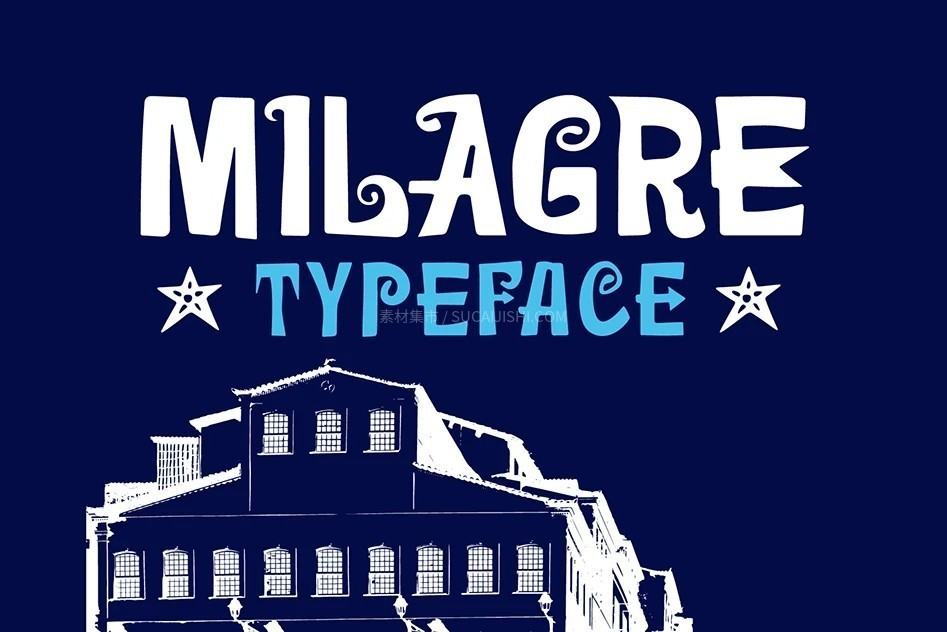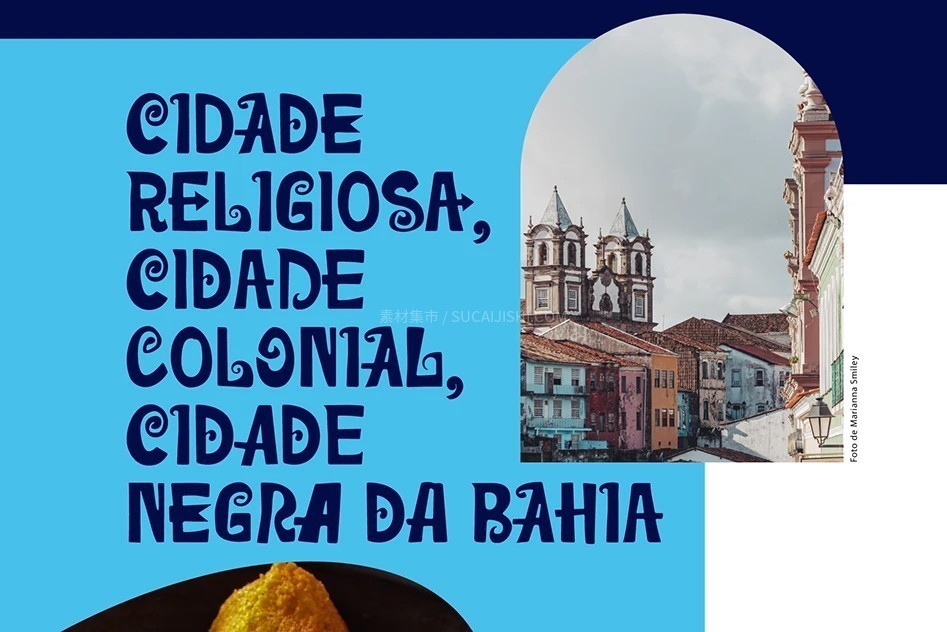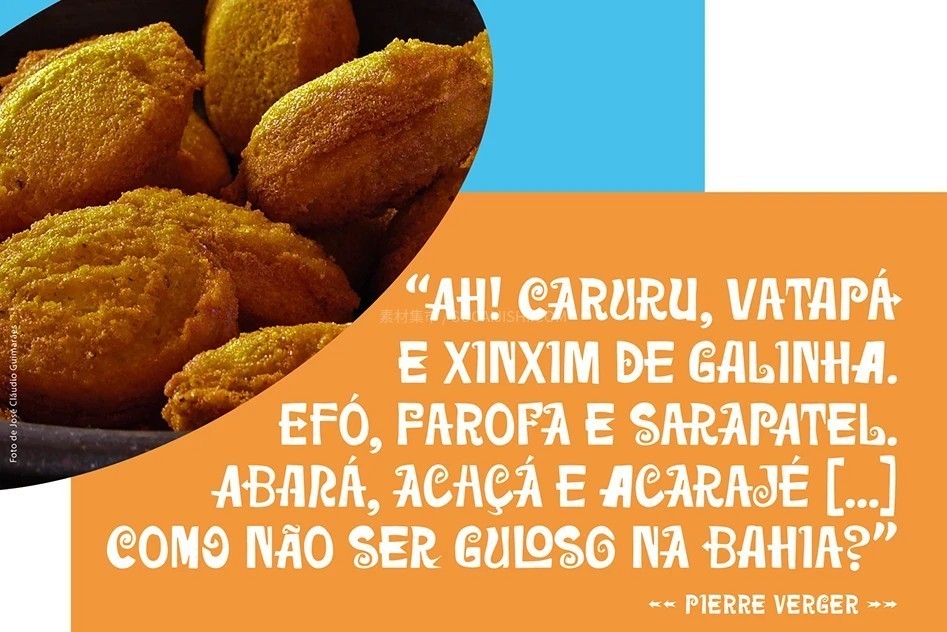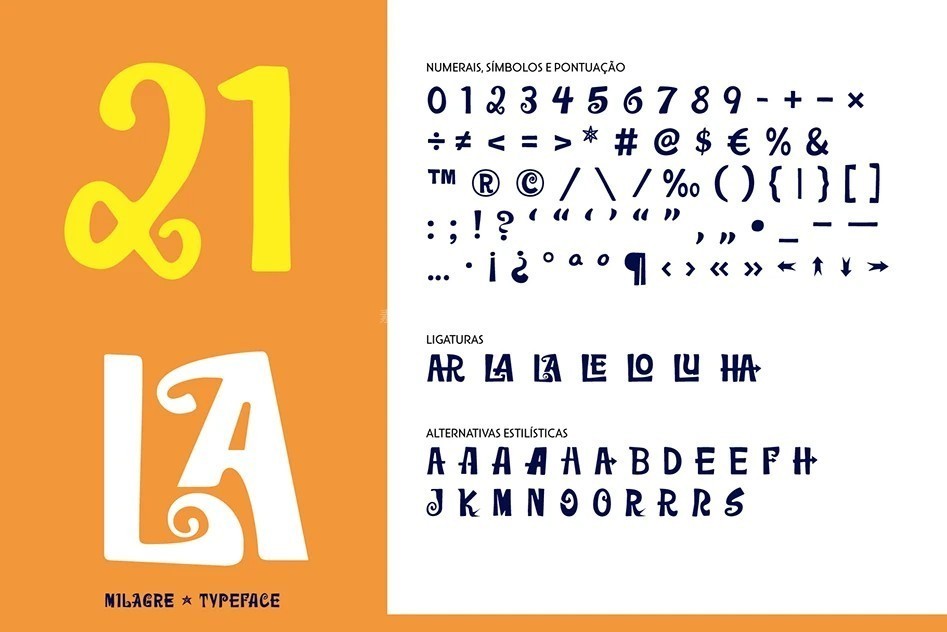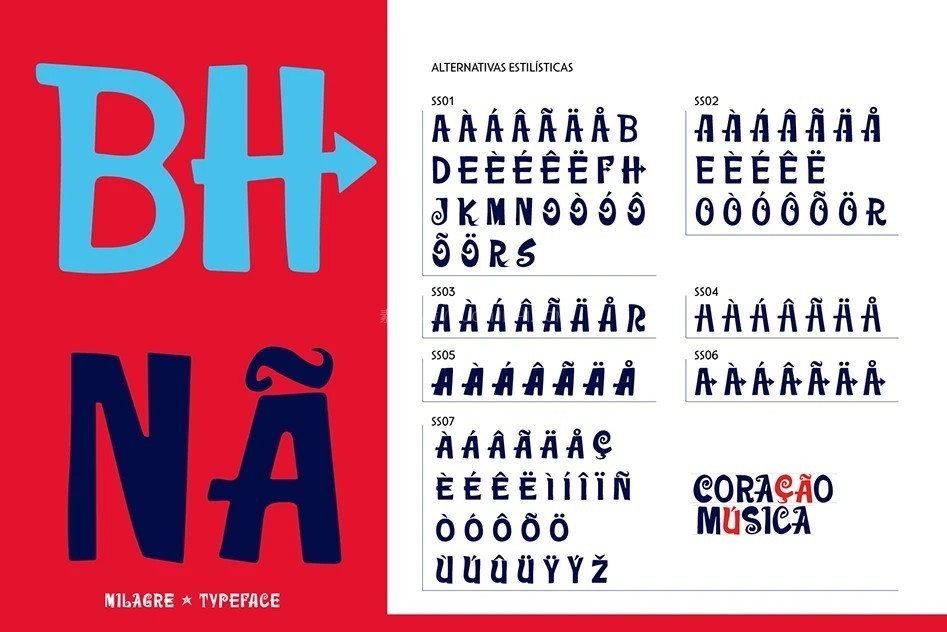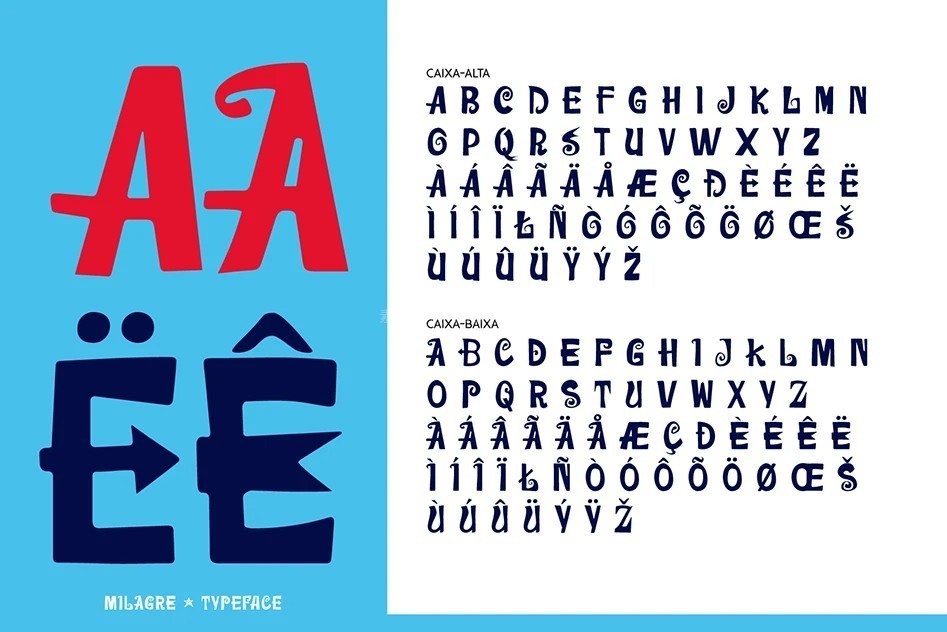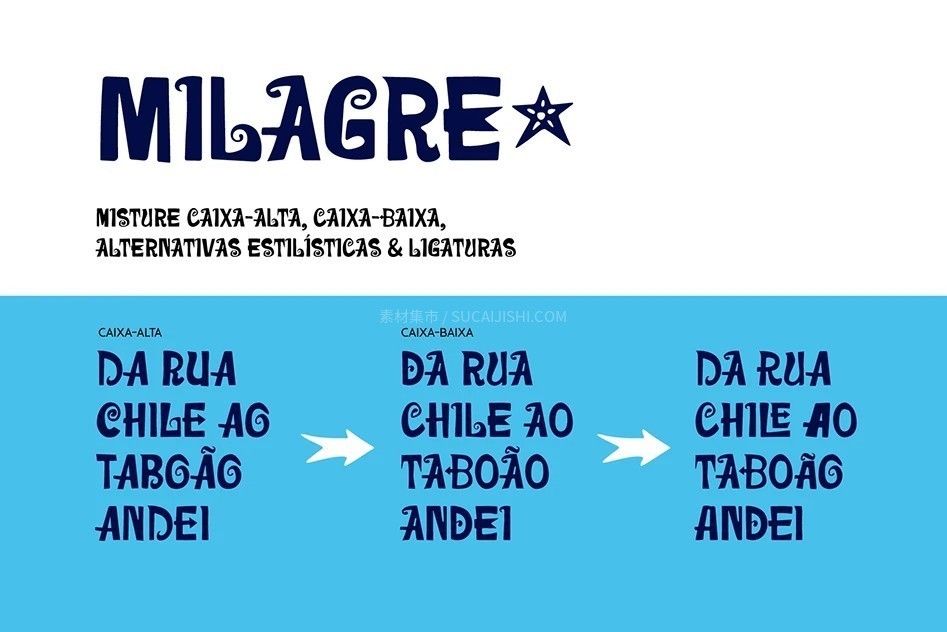
Milagre手作装饰英文字体,免费可商用
这是一款极具历史沉淀与地域色彩的装饰性显示字体。其灵感源自萨尔瓦多佩洛里尼奥广场(Largo do Pelourinho)著名的若热·阿马多之家基金会(Fundação Casa de Jorge Amado)外的瓷砖面板。
字体的灵魂跨越了文学与美术:文字内容出自作家 James Amado,字体原型由艺术家 Floriano Teixeira 亲手书写,并由陶艺大师 Udo Knoff 于 1987 年手工雕刻在瓷砖上。Milagre 将这种融合了手作温度与巴伊亚文化遗产的视觉语言,转化为现代数字排版中的艺术表达。